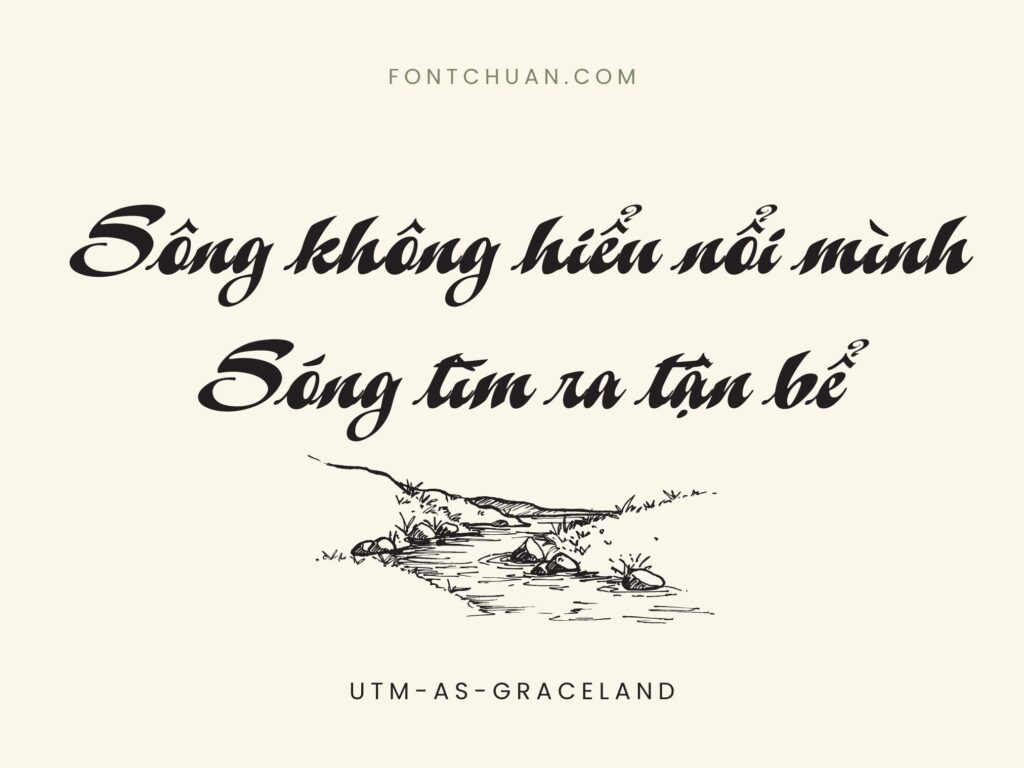
UTM A&S Graceland là một Font Script mang phong cách Font Handwritten mềm mại, thanh lịch và tự nhiên. Kiểu chữ này tái hiện lại nét viết tay uyển chuyển, giúp mỗi ký tự trở nên sống động và có chiều sâu cảm xúc. UTM A&S Graceland đã được Việt hóa, hỗ trợ đầy đủ tiếng Việt cùng hơn 100 ngôn ngữ khác. Đây là một trong những font được thành viên Font Chuẩn sưu tầm và chọn lọc kỹ lưỡng nhằm đáp ứng nhu cầu đa dạng của cộng đồng thiết kế.
UTM A&S Graceland có cấu trúc chữ với các nét uốn lượn nhẹ nhàng, tạo cảm giác gần gũi và thân thiện. Font này phù hợp cho các ứng dụng như thiết kế thiệp mời, tiêu đề, logo và các ấn phẩm in ấn yêu cầu sự tinh tế và cá nhân hóa. Các ngành nghề như quảng cáo, thiệp cưới, giáo dục và ẩm thực có thể tận dụng UTM A&S Graceland để tạo điểm nhấn độc đáo trong thiết kế.